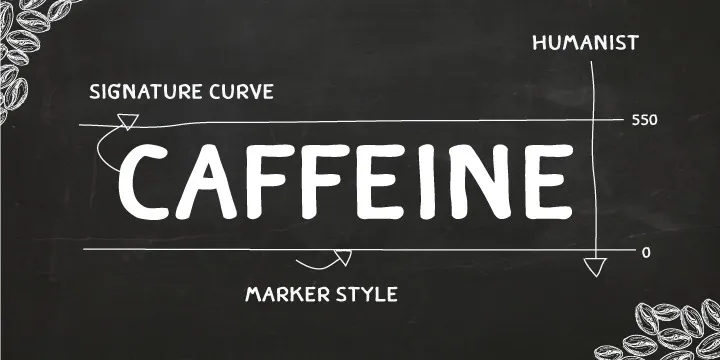
A Caffeine Font Family é uma escolha única para designers que buscam um estilo clean e moderno para seus projetos digitais. Este famoso conjunto de fontes sans-serif foi criado por Hamilton, oferecendo uma experiência visual versátil para textos em sites, aplicativos e redes sociais. A Caffeine traz alegria e conforto ao design digital com seu equilíbrio perfeito entre simplicidade e elegância, tornando-a não apenas um recurso gráfico eficaz, mas também uma fonte reconfortante que promete manter seus olhos direcionados para o conteúdo. Seja você criando materiais para um blog sobre tecnologia ou desenvolvendo uma plataforma de redes sociais, a Caffeine Font Family é uma ótima escolha para dar uma pitada de personalidade sem comprometer a legibilidade e a facilidade de uso dos textos.